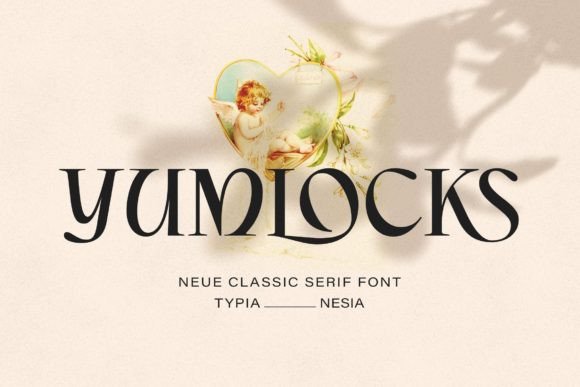
Yumlocks
Yumlocks – Font Modern Elegant yang Menambah Sentuhan Mewah
Yumlocks hadir sebagai font serif modern yang memadukan keanggunan klasik dengan sentuhan kontemporer. Dengan flourish dekoratif yang rapih, font ini cocok untuk:
- Undangan pernikahan, acara resmi, atau surat pribadi
- Branding produk mewah seperti parfum, perhiasan, atau fashion
- Desain editorial, majalah, atau materi promosi premium
Keunggulan Yumlocks
Berikut beberapa alasan mengapa Yumlocks menjadi pilihan utama para desainer:
- Desain Modern & Elegan – Mungkas garis tebal dengan lekukan lembut, memberi kesan anggun tanpa berlebihan.
- Flourishes Dekoratif – Detail hiasan pada huruf “Y”, “S”, dan “R” menambah karakter unik.
- PUA Encoded – Akunkan akses penuh ke semua glyphs dan ligatures, memudahkan integrasi simbol khusus.
Apa Itu PUA Encoding?
PUA (Private Use Area) adalah wilayah kode Unicode yang disediakan untuk penggunaan khusus. Dengan menggunakan PUA encoding, Yumlocks memungkinkan:
- Penggunaan glyph tambahan yang tidak standar, sehingga desain Anda tetap unik.
- Ligatures eksklusif yang memudahkan kombinasi karakter secara visual.
- Fleksibilitas tinggi dalam produksi cetak dan digital.
Kesimpulan: Pilihan Terbaik untuk Proyek Mewah
Yumlocks bukan sekadar font; ia adalah pernyataan gaya. Dengan kombinasi elegan, flourishes dekoratif, dan dukungan PUA encoding, font ini memberi Anda kebebasan kreatif sekaligus tampilan profesional. Apakah Anda sedang menyiapkan undangan eksklusif atau merek mewah, Yumlocks siap menambah sentuhan kelas dan kesan premium pada setiap proyek.